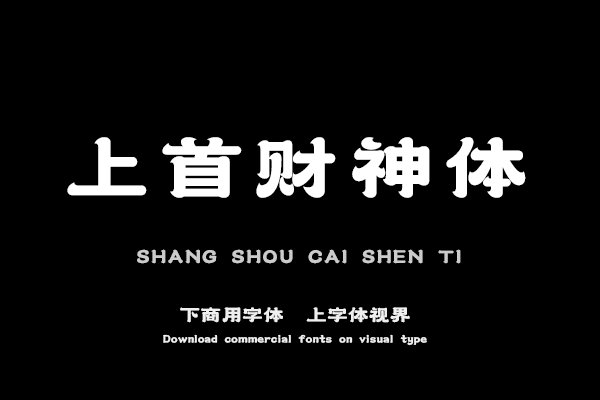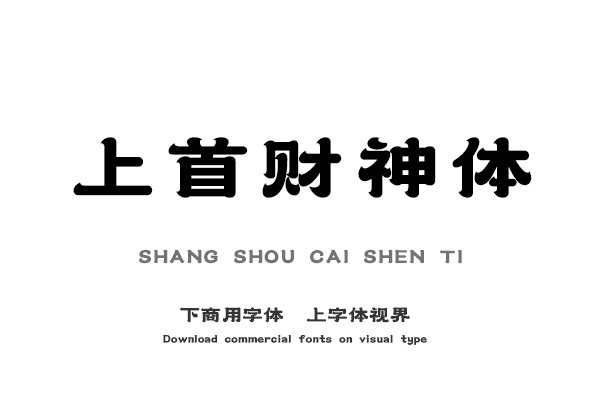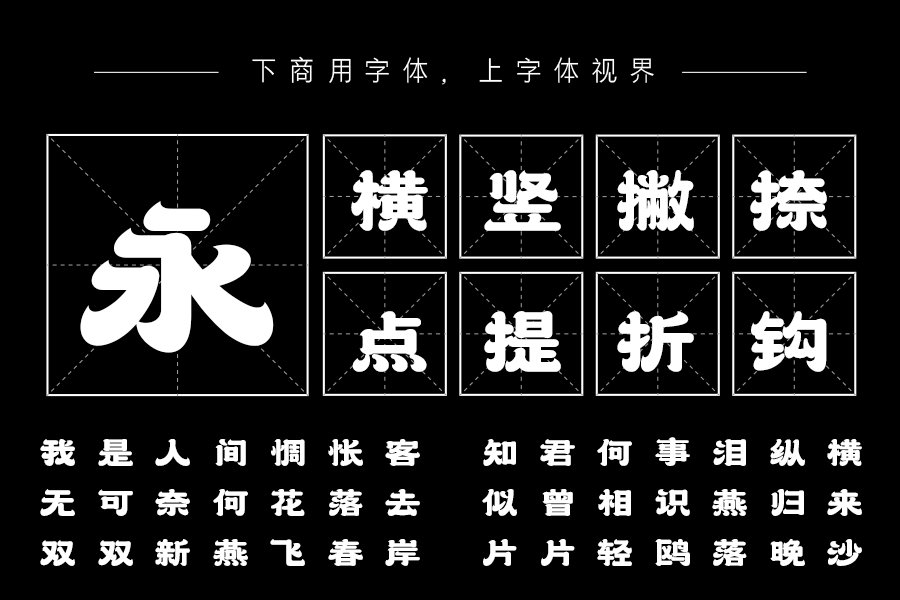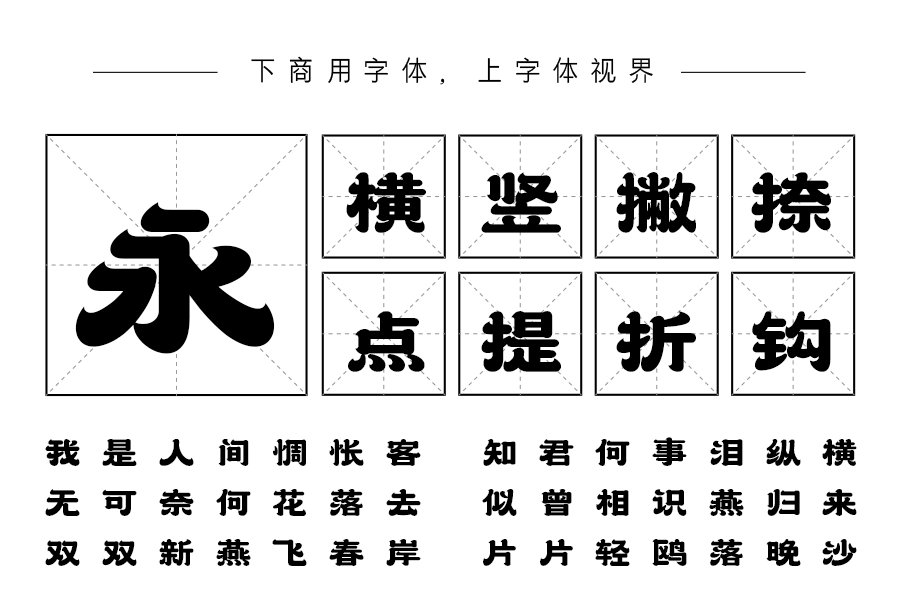
上首财神体,简体中文约6763字,字体笔画圆润饱满,撇捺曲线流畅,字体风格中式又新颖。给人喜庆又吉祥的感觉。适用于搭配标志、广告标语、商业广告等高端属性。购买须知:“下载服务费”与“字体VIP”所获得字体 仅用于个人非商用, 商用请联系付费授权。本字体为电脑用字,手机没有root权限不支持直接手机换字(手机如何root,请自行百度搜索教程)。购买前请先 了解清楚后再付款 ,字体为虚拟产品无法回收 一旦购买不支持退款。